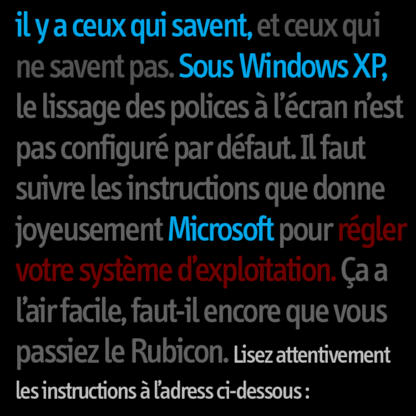
Polices lissées sous Windows XP
L’adresse des conseils de Microsoft pour régler vos préférences système qui permettront de lisser vos caractères sans avoir ces affreux pixels qui fatiguent considérablement la vue, même si certains les considèrent à titre expérimental comme des proto-typographie. ;-)